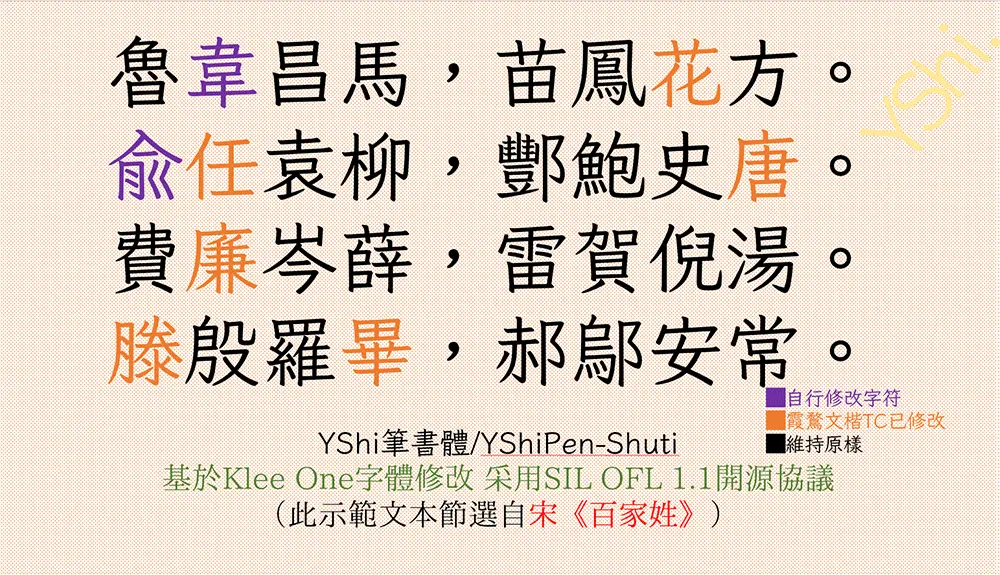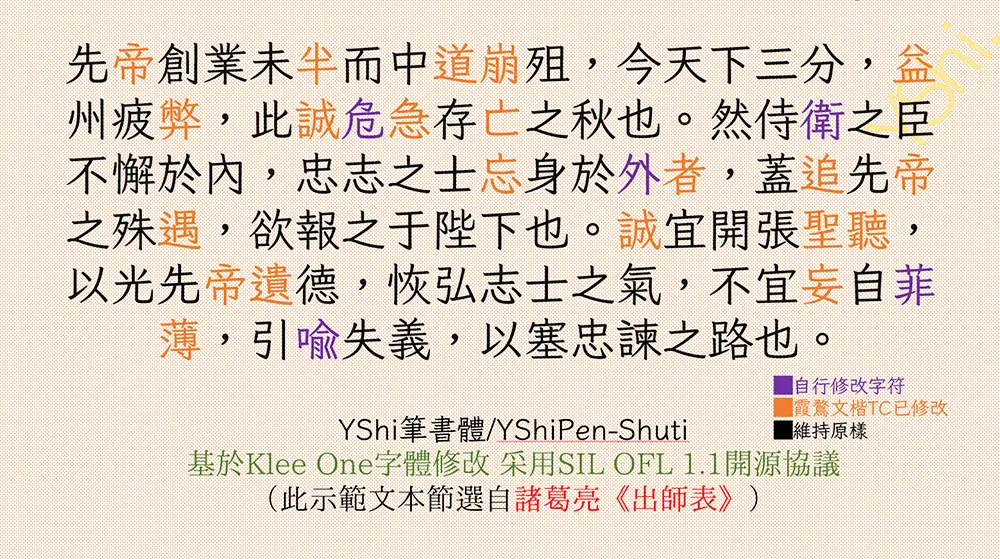
YShi新筆書預覽
YShi新筆書介紹
2020 年 12 月,日本著名字體廠商 FONTWORKS 在 GitHub 上釋出了 7 款開源日文字體,其中 Klee One 字符數最多,兼有仿宋和楷體的特點,具有優雅的外觀及較高的可讀性,非常適合正文排版。此外,該字體擁有多種衍生版本,提供了更多對字形的選擇性,以及增加了更多字符, 然而,仍然或多或少缺字, 此外,對於字形的選擇,這些字形也不能滿足所有人的口味。
YShi筆書體(YShiPen-Shuti)是基於 Klee One 進行字符擴展及補充的項目。該項目於2022 年 12 月試運行,於23年夏天正式發佈第一版,起初目的是修改成偏向於康熙、98細明體標準的字形,並對Klee、霞鶩文楷TC進行擴充,主要是囊括基本區更多字符(不直接使用文楷原版煉丹的字符,而是手拼)且以舊字形展現。
本字體不嚴格遵循《傳承字體檢校表》推薦寫法,而是對其進行取捨
本字體異體版少許借用碑帖中的某些異體字